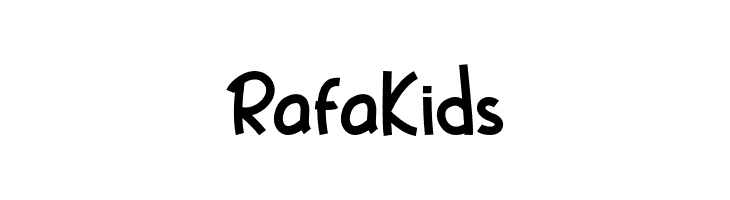
A bold, distressed font with a vintage, rugged appearance.
A clean, geometric font with a modern and minimalist design.
A bold, playful font with rounded, hand-drawn characters.
A modern, rounded font with a slight diagonal slant and smooth strokes.
A bold, distressed font with a grunge aesthetic.
A bold, jagged Halloween-themed decorative font with spooky icons.
A modern serif font with playful curves and sharp edges.
A playful, handwritten font with a whimsical and friendly appearance.
A lively, handwritten-style font with bold, expressive strokes.
A whimsical, handwritten font with playful curls and loops.
A modern, italic font with sharp, angular edges and a dynamic style.
A classic blackletter font with bold, angular letterforms and a narrow design.
A futuristic, geometric font with bold, rounded shapes and tight spacing.
A geometric, futuristic outlined font with a technical and modern appearance.
A bold, decorative font with Victorian-inspired flourishes.
A bold, expressive brush-style font with dynamic, hand-painted strokes.
A playful and bold font with thick strokes and whimsical shapes.
Playful handwritten font with rounded edges.
A playful, bold, hand-drawn font with outlined characters.
A bold, 3D italic font with outlined characters and a modern, dynamic style.
A playful, hand-drawn font with a whimsical and dynamic style.
A playful, bold handwritten font with a casual and friendly style.
A bold, edgy font with sharp, angular accents resembling barbed wire.
A bold, high-contrast serif font with a classic yet modern appeal.
A bold, italicized handwritten font with smooth curves and a playful style.
A bold, handwritten font with a casual and playful style.
A sleek, modern italic font with smooth curves and consistent stroke thickness.